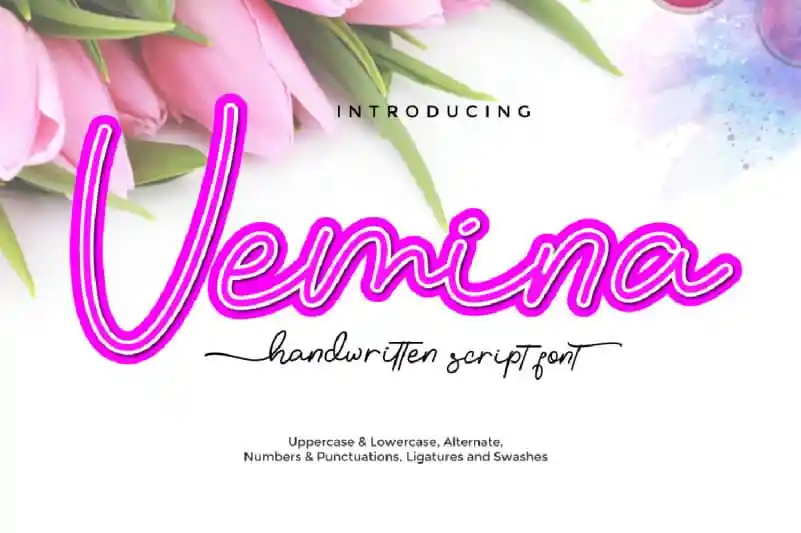
Vemina Handwritten Scipt Font – Fonte Grátis
Vemina Handwritten Scipt Font
A Vemina é uma fonte script curvilínea que traz ao design um ar de elegância e naturalidade perfeitos para assinaturas delicadas. Ela foi criada com movimentos naturais, resultando em linhas monolineares suaves e detalhes finos que remetem à arte do traçado manual. Ideal para uso em materiais digitais como cartões de aniversário personalizados ou websites de estilos pessoais, a Vemina é perfeita para quem valoriza o toque humano na sua marca digital. Seja você um designer gráfico criando design editorial, ou alguém que busca dar um toque único ao seu trabalho, Vemina é uma escolha excelente para aqueles que buscam um equilíbrio entre elegância e versatilidade no seu font library.